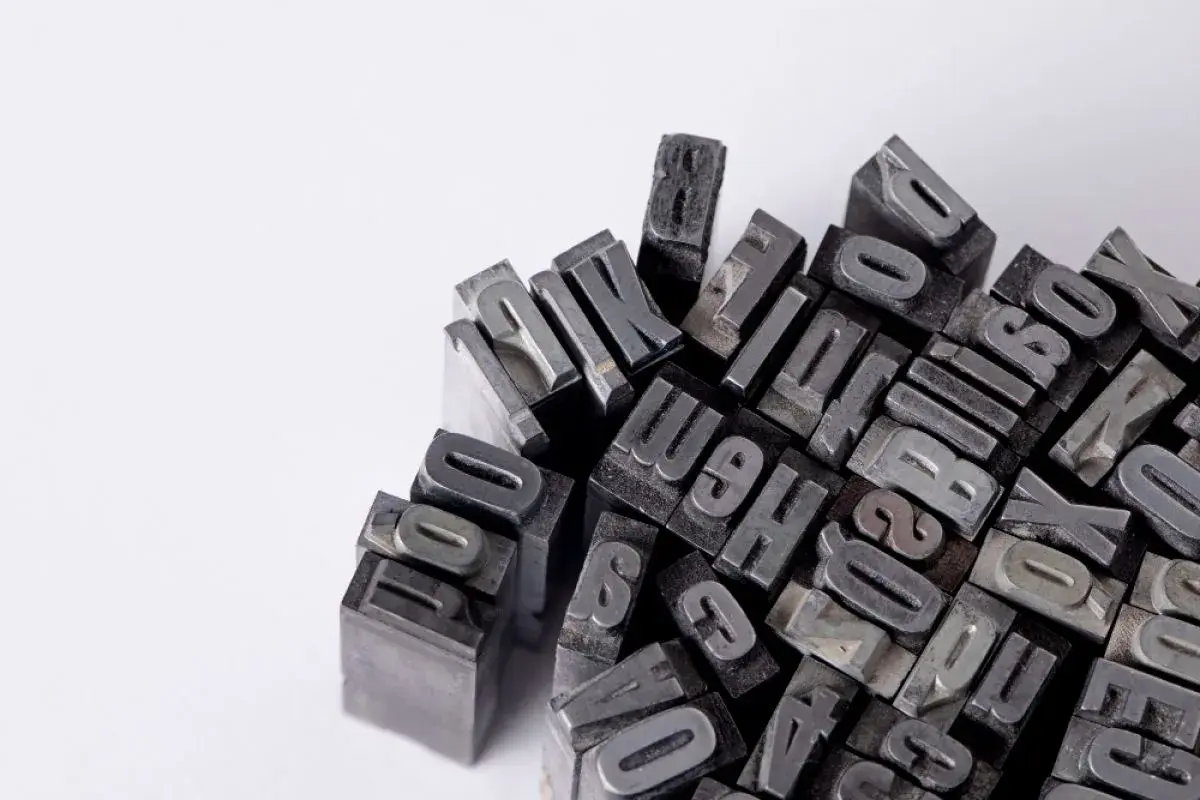
Typografia w druku pracuje inaczej niż na ekranie: litery muszą być czytelne z konkretnej odległości, na różnym papierze i w często bardzo małym formacie. Dobre czcionki drukarskie nie są tylko ozdobą projektu; wpływają na wiarygodność marki, tempo czytania i to, czy ulotka, menu albo katalog naprawdę zachęcą do działania. W tym tekście pokazuję, które kroje sprawdzają się najlepiej w profesjonalnym składzie, jak dobrać je do rodzaju materiału i jakie błędy najczęściej psują efekt.
Najważniejsze zasady, zanim wybierzesz krój do druku
- W druku najpierw liczy się czytelność, dopiero potem charakter kroju.
- Szeryfowe pisma zwykle lepiej pracują w dłuższym tekście, a bezszeryfowe w krótkich komunikatach i nagłówkach.
- Przy tekście ciągłym bezpieczny punkt wyjścia to 120-140% interlinii i 45-75 znaków w wierszu.
- Do materiałów reklamowych dla lokalnych firm najlepiej działa prosty układ: jedna rodzina do tekstu, druga do nagłówków.
- Przed drukiem trzeba sprawdzić polskie znaki, osadzenie fontów w PDF i próbny wydruk na podobnym papierze.
Co naprawdę decyduje o czytelności kroju w druku
Ja przy wyborze kroju zaczynam od pytania, z jakiej odległości ktoś będzie go czytał i ile czasu ma na to odbiorca. To ważniejsze niż sam efekt „ładności”, bo plakat ogląda się inaczej niż wizytówkę, a menu w restauracji inaczej niż ofertę hurtową.
Na odbiór wpływają przede wszystkim trzy rzeczy. Po pierwsze, wielkość tekstu względem formatu. Po drugie, kontrast i grubość kresek, bo zbyt cienki krój może zniknąć na papierze. Po trzecie, jakość samego fontu, czyli to, czy ma pełny zestaw znaków, poprawne odstępy i dobrze zaprojektowane polskie litery.W praktyce materiał do czytania z bliska może pozwolić sobie na większą subtelność, ale plakat, szyld czy roll-up potrzebują prostszego, mocniejszego rysunku liter. Na papierze niepowlekanym litery wyglądają bardziej miękko, a cienkie elementy łatwiej tracą ostrość. Im gorszy papier i bardziej dynamiczna produkcja, tym bezpieczniej postawić na krój o większej masie i wyraźniejszym kształcie.
Warto też pamiętać o polskich znakach. To detal, który wielu osobom wydaje się oczywisty, a potem w wydruku wychodzą dziwne wersje liter albo ręcznie „doklejane” ogonki. Przy materiale reklamowym wygląda to od razu amatorsko. Gdy to już jest jasne, można przejść do konkretnych rodzin krojów.
Najważniejsze rodziny krojów i kiedy się sprawdzają
Jeśli miałbym uprościć temat do praktyki, powiedziałbym tak: w druku najczęściej wybiera się jedną z kilku rodzin krojów, a różnica między nimi ma większy wpływ na odbiór niż drobne dekoracje.
| Rodzina kroju | Najlepsze zastosowanie | Co daje w druku | Na co uważać |
|---|---|---|---|
| Szeryfowe | Dłuższe teksty, katalogi, raporty, eleganckie materiały | Prowadzą wzrok, dają wrażenie klasy i stabilności | Przy małej wielkości i słabym papierze mogą się zamazywać |
| Bezszeryfowe | Ulotki, plakaty, cenniki, nagłówki, komunikaty promocyjne | Są czyste, nowoczesne i bardzo czytelne w krótkich formach | W długim składzie bywają chłodniejsze i mniej „literackie” |
| Slab serif | Promocje, marki rzemieślnicze, komunikacja z mocnym charakterem | Budują wyrazistość i dobrze pracują na plakatach oraz witrynach | Łatwo je przeciążyć, jeśli projekt jest zbyt ciężki |
| Display | Duże nagłówki, okładki, key visuale | Tworzą osobowość i od razu przyciągają uwagę | Nie nadają się do dłuższego czytania |
| Script i handwriting | Zaproszenia, logo, subtelne akcenty | Dodają emocji, miękkości i indywidualności | W małym rozmiarze szybko tracą czytelność |
| Monospace | Materiały techniczne, instrukcje, styl retro | Wprowadzają porządek i specyficzny klimat | Rzadko są najlepszym wyborem do zwykłej reklamy |
Jak podaje Monotype, najczęściej wraca się do kilku podstawowych grup, przede wszystkim serif, sans, script i slab. To dobry punkt wyjścia, bo w praktyce właśnie te rodziny rozwiązują większość problemów w projektach drukowanych, od oferty usługowej po prostą reklamę lokalną.
Sama rodzina kroju to jednak dopiero połowa pracy. Równie ważne są parametry składu.
Parametry składu, które robią największą różnicę
Nawet dobry font można zepsuć zbyt małym stopniem pisma, ciasną interlinią albo zbyt długimi wierszami. To właśnie na tym etapie najczęściej widać, czy projekt składał ktoś, kto rozumie druk, czy ktoś, kto po prostu przepisał tekst z ekranu.
| Element | Praktyczny zakres | Dlaczego to ma znaczenie |
|---|---|---|
| Tekst główny | Najczęściej 9-11 pt, przy dłuższych materiałach zwykle bliżej górnej granicy | Zbyt mały stopień męczy wzrok i psuje odbiór jakości |
| Interlinia | 120-140% wielkości pisma | Daje oddech między wierszami i poprawia czytanie bloków tekstu |
| Długość wiersza | Około 45-75 znaków | Zbyt długie linie spowalniają czytanie, zbyt krótkie rozbijają rytm |
| Waga kroju | Regular lub medium jako baza, light tylko ostrożnie | Za cienkie litery gorzej znoszą papier i druk |
| Kerning i tracking | Drobna korekta w nagłówkach, bez przesady w tekście ciągłym | Porządkują odstępy i zapobiegają zlepieniu liter |
Kerning reguluje odstęp między konkretnymi parami liter, a tracking rozsuwa albo zagęszcza cały blok tekstu. W druku różnica jest bardziej widoczna niż na monitorze, bo oko natychmiast wyłapuje zbyt ciasne litery lub nagłówek, który wygląda na rozbity.
Jeśli projekt ma budować poczucie jakości, zwykle wolę prosty układ z jedną rodziną do tekstu i drugą, wyraźniejszą, do nagłówków. Więcej krojów rzadko daje lepszy efekt, a częściej tylko wprowadza chaos. Kiedy skład jest już ustawiony, trzeba go dopasować do rodzaju materiału.
Jak dobrać krój do materiału reklamowego
W lokalnym marketingu nie projektuje się typografii „dla zasady”. Projekt ma działać na konkretnym nośniku. Inaczej ustawiam tekst dla pizzerii, inaczej dla biura rachunkowego, a jeszcze inaczej dla salonu usługowego, który potrzebuje szybkiego skojarzenia z jakością.
| Materiał | Najlepszy kierunek | Dlaczego to działa |
|---|---|---|
| Ulotka promocyjna | Bezszeryfowy nagłówek i prosty krój tekstowy | Treść musi być przeczytana szybko, bez wysiłku |
| Wizytówka | Minimalistyczny sans albo elegancki serif | Mało miejsca, więc liczy się porządek i wysoka czytelność |
| Menu restauracji | Humanistyczny sans lub spokojny serif | Gość powinien skanować pozycje, a nie walczyć z układem |
| Plakat lub roll-up | Mocny display na nagłówku, neutralny font w informacji dodatkowej | Najpierw ma uderzać przekaz, potem szczegóły |
| Katalog lub broszura | Szeryfowy krój do dłuższych partii tekstu lub spokojny sans | Pomaga utrzymać rytm czytania i wygląda profesjonalnie |
| Szyld lub witryna | Prosty, mocny sans, często w wersji pogrubionej lub kondensowanej | Tekst musi być czytelny z dystansu i w ruchu |
Najczęstsze błędy, które widać dopiero na wydruku
W praktyce to nie brak „ładnego fontu” niszczy projekt, tylko kilka powtarzalnych potknięć. I niestety właśnie one najczęściej wychodzą dopiero po wydruku, kiedy poprawa kosztuje więcej czasu i pieniędzy niż powinna.
- Zbyt wiele krojów - mieszanie trzech, czterech i pięciu fontów prawie zawsze rozbija spójność.
- Ozdobny font w małym rozmiarze - wygląda efektownie na ekranie, ale w druku szybko staje się nieczytelny.
- Za cienka kreska - szczególnie ryzykowna na papierze niepowlekanym i w drobnych podpisach.
- Brak polskich znaków - kończy się wizualnym błędem, który od razu obniża poziom projektu.
- Za mały kontrast - jasny tekst na jasnym tle albo ciemny na ciemnym zawsze będzie problemem.
- Brak osadzenia fontów - plik może otworzyć się inaczej na innym komputerze lub po stronie drukarni.
- Test tylko na monitorze - ekran często wybacza więcej niż papier, więc próbny wydruk naprawdę ma sens.
Według Adobe osadzenie fontów w PDF ogranicza ryzyko, że drukarnia podmieni krój na inny podczas otwierania lub drukowania pliku. Dla mnie to jeden z tych drobnych kroków, które wyglądają technicznie, ale realnie chronią wygląd całej publikacji.
Na koniec zostaje jeszcze szybka kontrola przed wysyłką pliku do drukarni.
Ostatnia kontrola przed wysłaniem projektu do drukarni
Gdy projekt jest już złożony, robię krótką kontrolę, która oszczędza najwięcej nerwów: sprawdzam rozmiary tekstu, polskie znaki, osadzenie fontów, zgodność kolorów i próbny wydruk na podobnym papierze. Jeśli coś ma być czytelne w biegu - na ulotce, cenniku, menu czy plakacie - lepiej wykryć problem przed eksportem niż po odbiorze nakładu.
- Czy tekst główny da się przeczytać bez powiększania?
- Czy nagłówki są mocniejsze, ale nie przytłaczają reszty układu?
- Czy w pliku nie ma przypadkowych zamienników kroju?
- Czy wiersze nie są zbyt długie i nie męczą oka?
- Czy projekt po wydruku nie traci kontrastu na wybranym papierze?
- Czy PDF wygląda tak samo po otwarciu na innym komputerze?
Jeśli miałbym zostawić jedną zasadę na koniec, byłaby prosta: w druku najlepiej działa typografia, której nie trzeba tłumaczyć. Kroje mają wspierać komunikat, a nie z nim konkurować. W materiałach promocyjnych dla lokalnych firm właśnie ta dyscyplina robi największą różnicę - odbiorca ma od razu widzieć porządek, profesjonalizm i sens, a nie zastanawiać się, czy projekt przypadkiem nie został przeciążony formą.